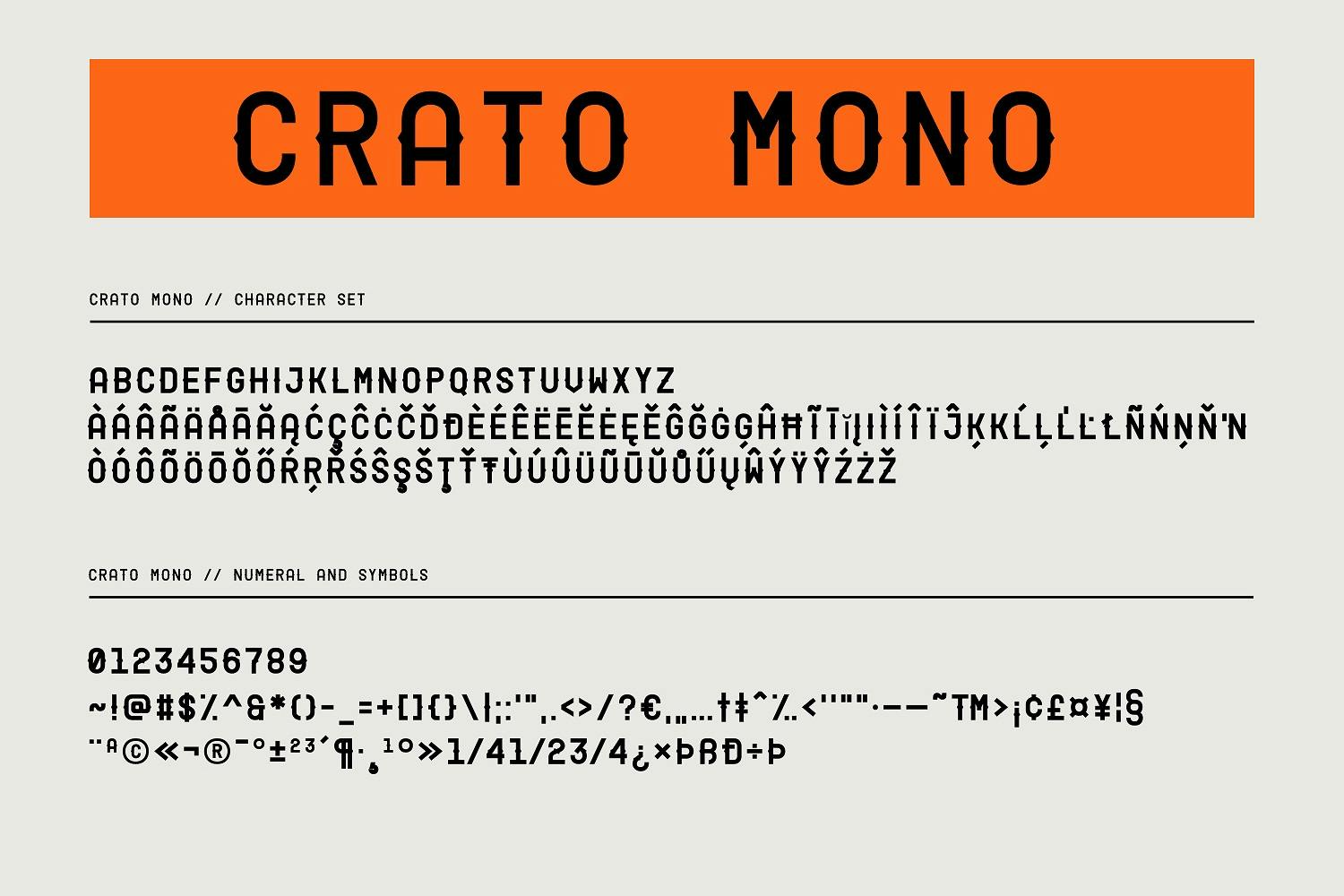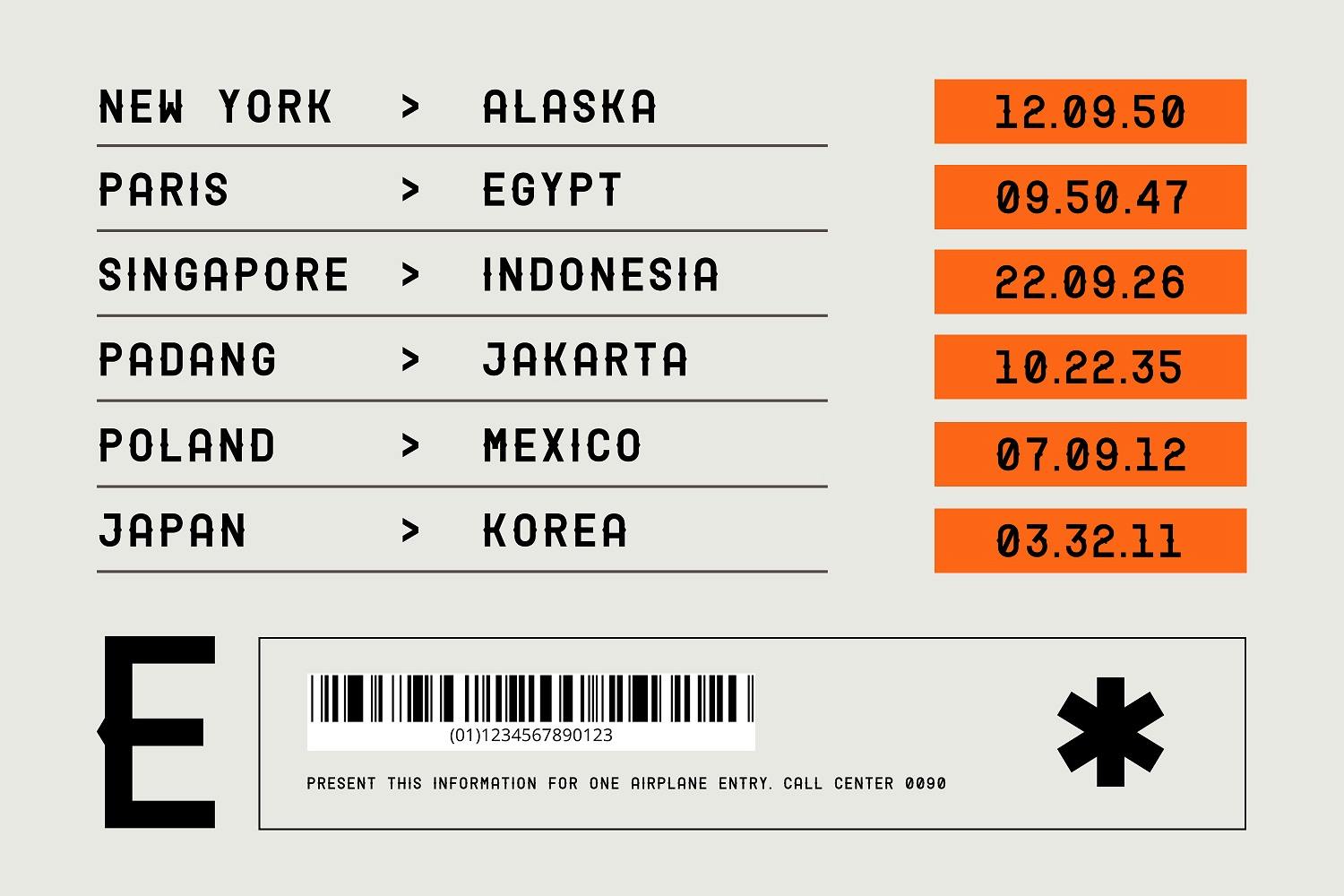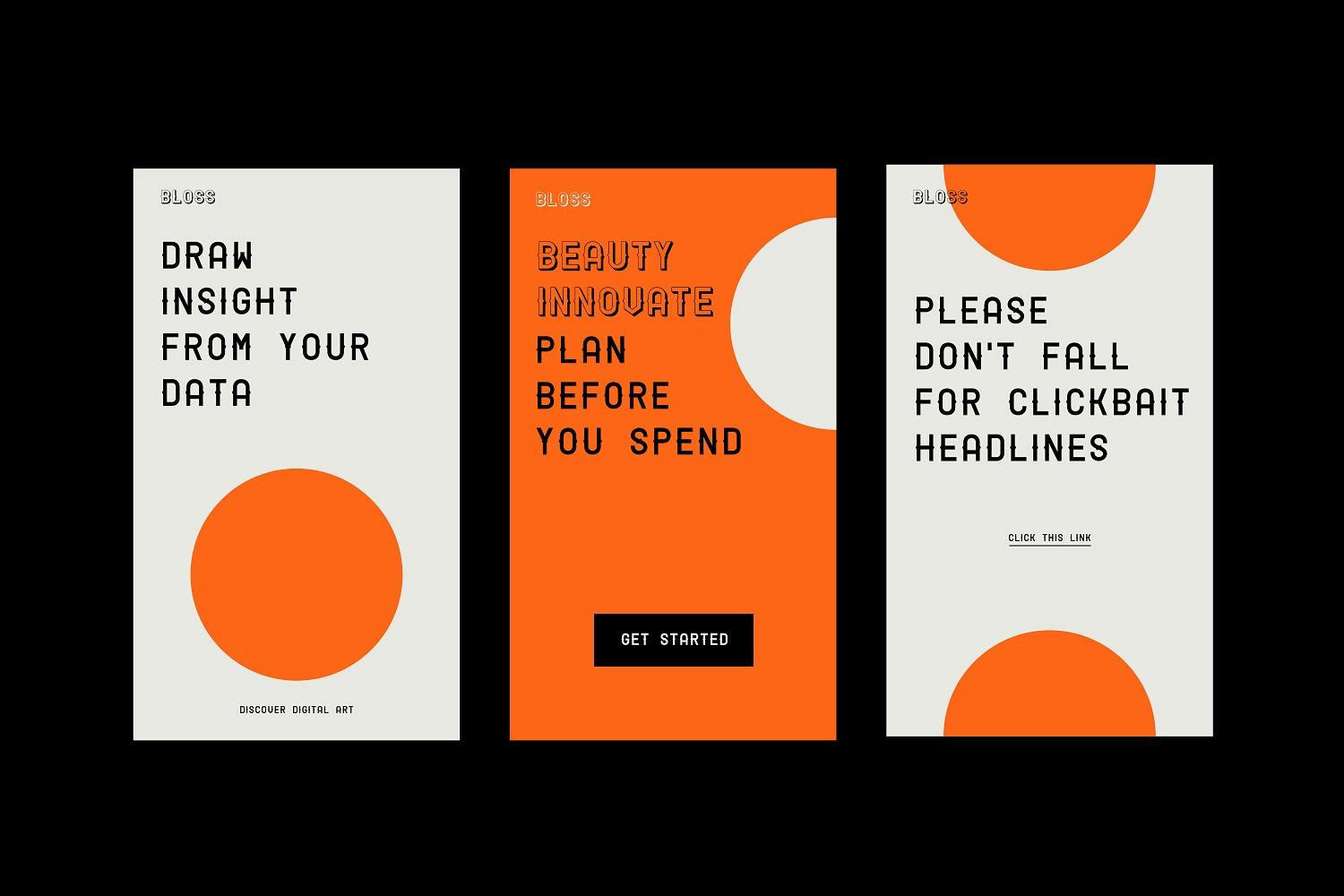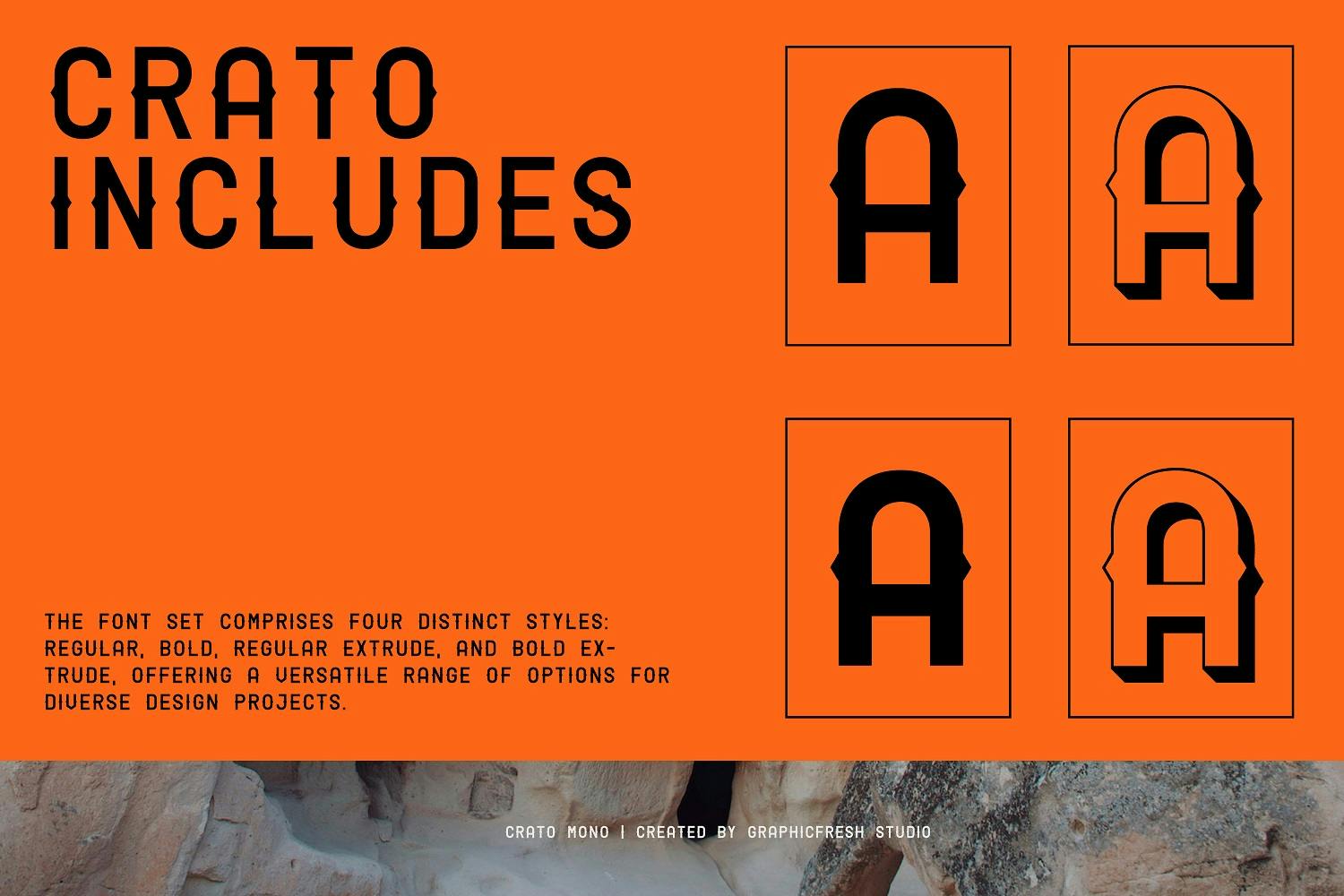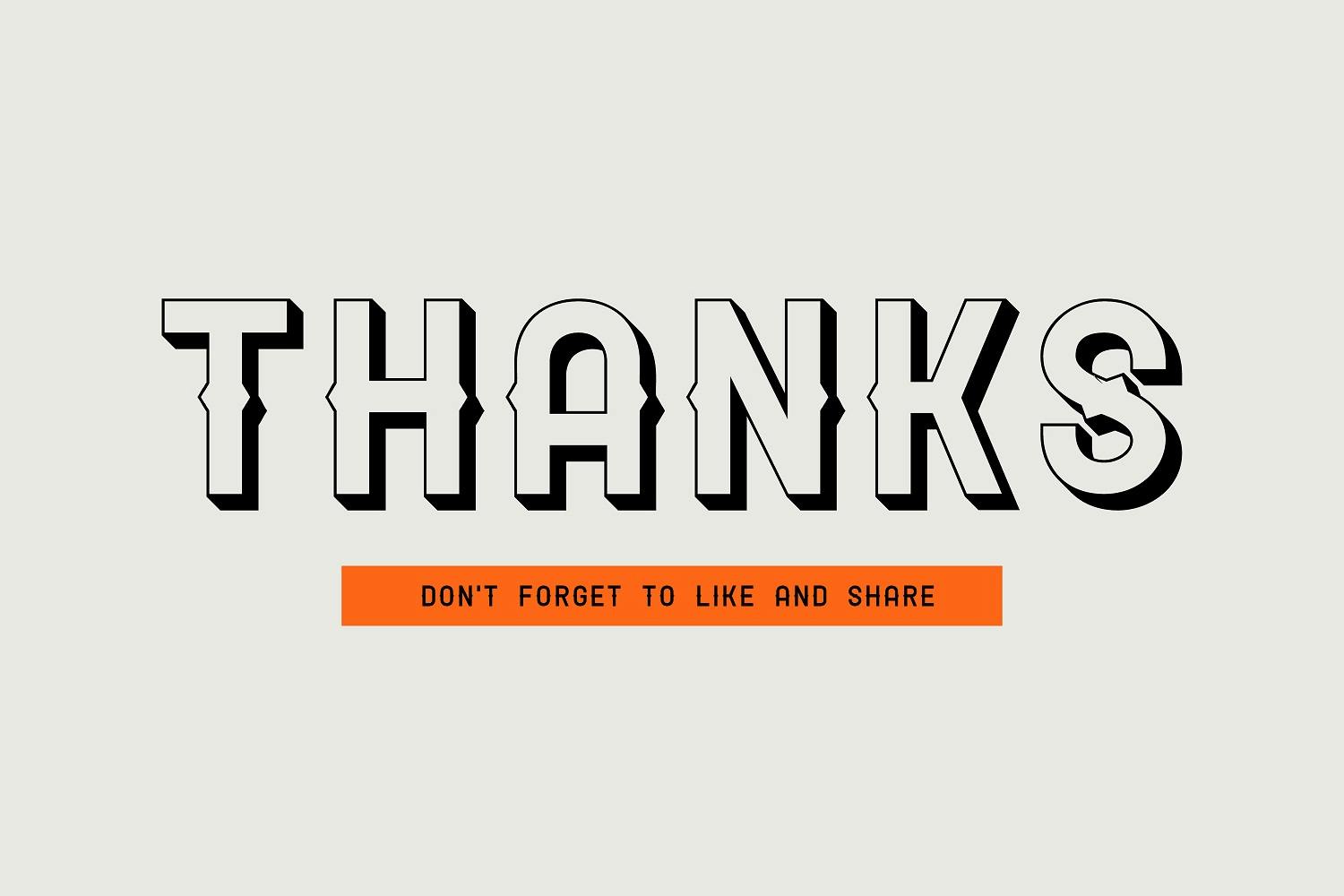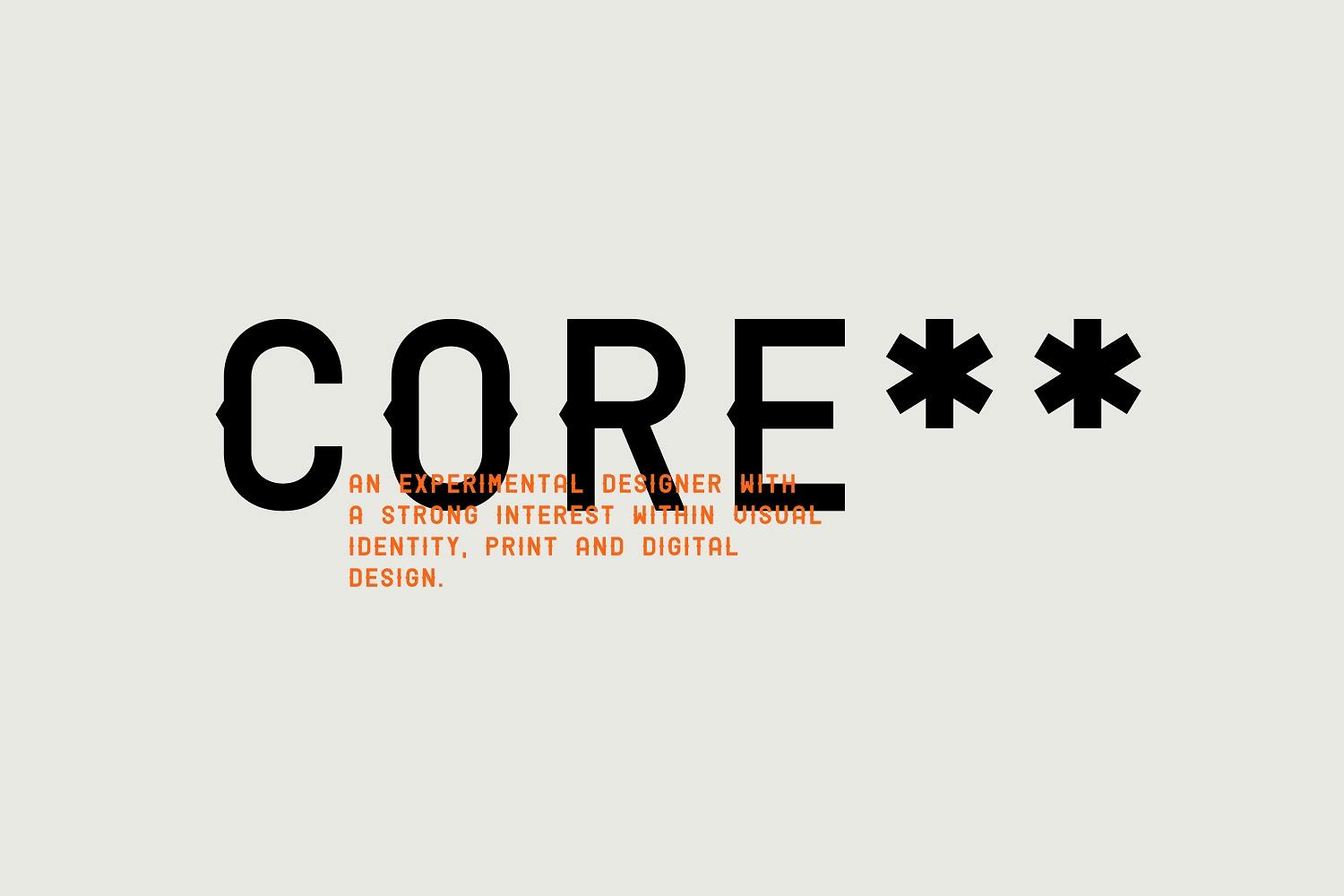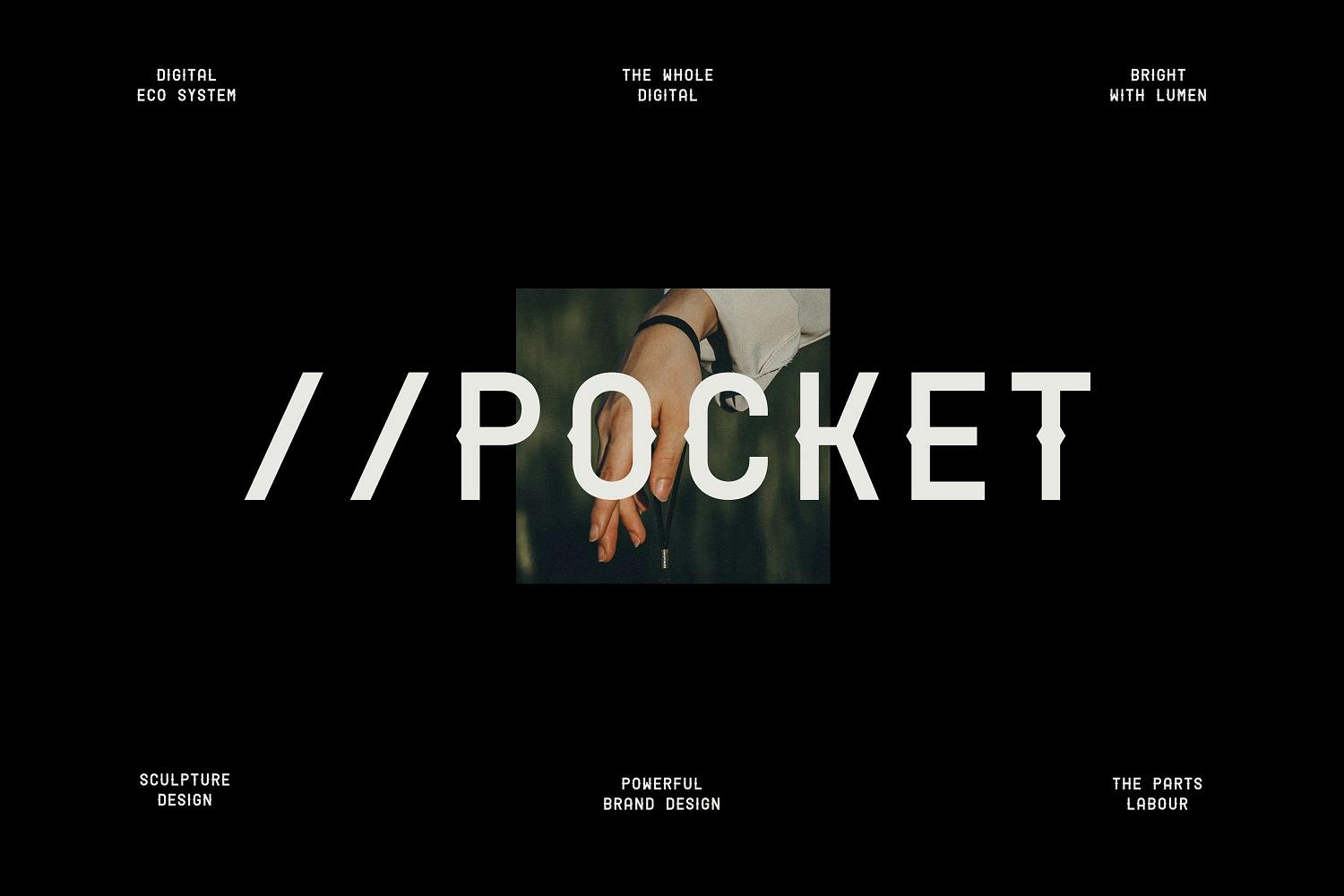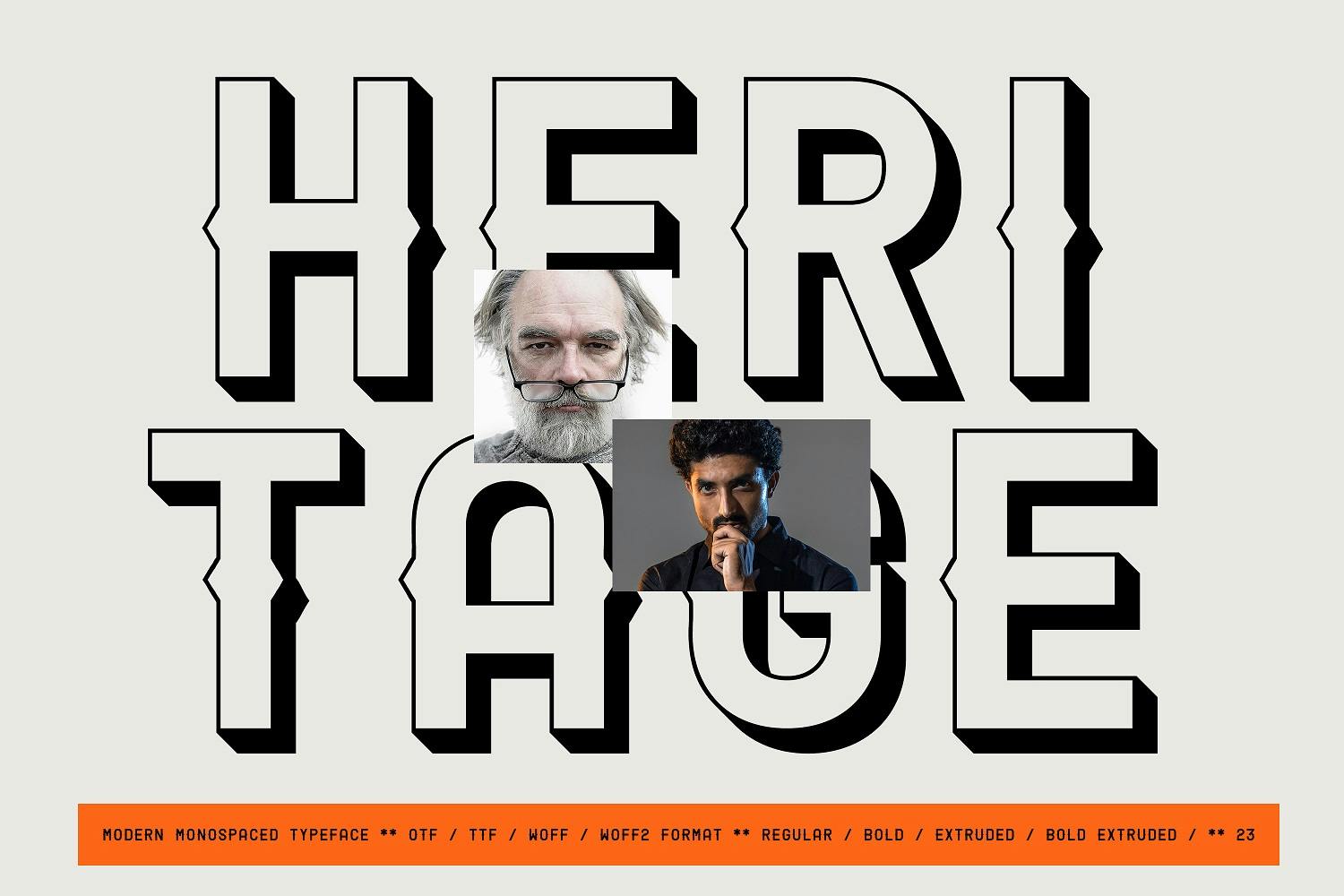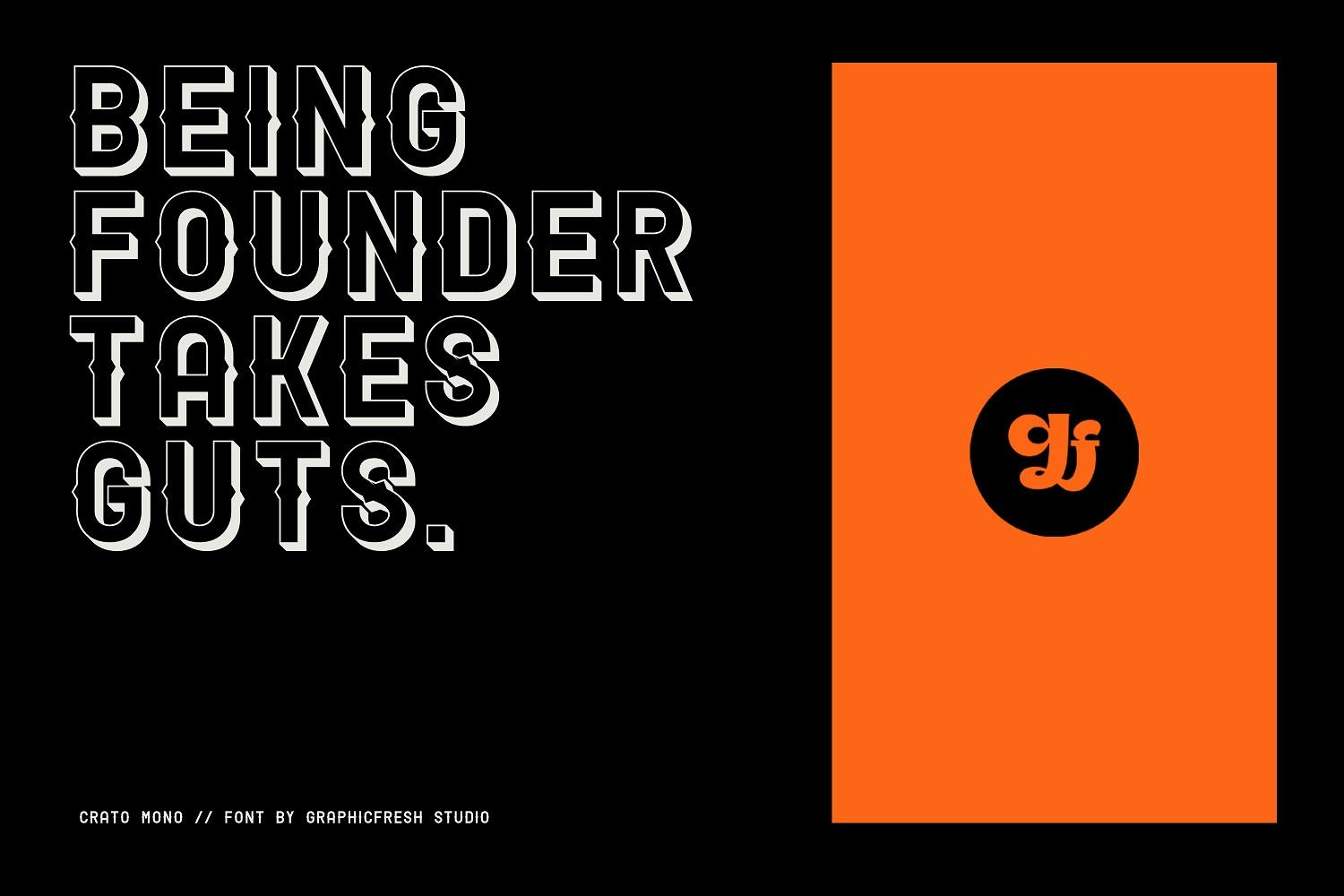
فونت کراتو مونو - فونت مدرن مونو اسپیس
با کشف ترکیب بینظیر طراحی کلاسیک و مدرن با فونت مونو اسپیس چندکاره ما. این فونت با جذابیت همیشگی و سبک سنس سریف، به راحتی هم جذابیت vintage و هم زیباییشناسی معاصر را به تصویر میکشد.
با سبک خاص و جذابیت چندمنظورهاش، این فونت به هر طراحی حسی از نوستالژی اضافه میکند، چه در حال طراحی یک لوگوی الهامبخش از گذشته باشید و چه یک وبسایت شیک.